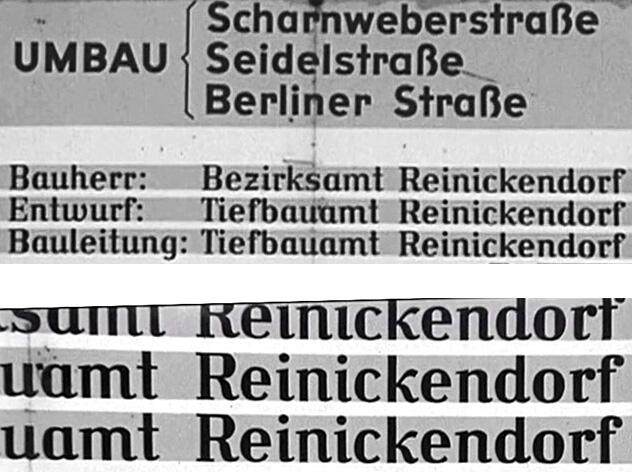
Bauschild-Schrift von 1960/61
Ich würde gern ein Bauschild aus dem Jahr 1960 (oder 61) digital "nachbauen", da leider keine gute Qualität in SW vorliegt.
Leider bin ich auch nach Ausprobieren dreier verschiedener Fontfinder (whatfontis, whatthefont und fontmatcherator) nicht annähernd fündig geworden.
Häufig wird ja bei der Suche nach älteren Schriften darauf verwiesen, daß es sich um Arbeiten eines Schildermalers handelte, was ja auch oft gut erkennbar ist an den teilweise sich unterscheidenden Formen eines im Text wiederkehrenden Buchstaben, z. B. e usw.
Auf den Ausschnitten (siehe Screenshot) des Bauschildes wird der Name "Reinickendorf" 3x untereinander wiederholt. Ich - als Laie - vermag hier keine Abweichungen einzelner Buchstaben von Zeile zu erkennen ... Daher gehe ich eigentlich nicht von einer Schildermaler-Schrift aus.
Augenfällig sind meiner Ansicht nach das unten leicht geschwungene kleine "w" im Wort Entwurf und der kleine Buchstabe "k", aber auch das kleine z mit Querstrich fällt zumindest heutzutage auf.
Auch hinsichtlich der serifenlosen Fettschrift am Kopf des Schildes "UMBAU" + 3 Straßennamen bin ich in keinem Fontfinder fündig geworden.
Besonders das runde a und das r mit dem nach unten gezogenen Bogen fallen hier auf. Runde a wurden hauptsächlich in Kursivschriften angezeigt, aber keine davon ähnelte auch nur ansatzweise der hier verwendeten Schrift.
Schilderhersteller nutzten aber auch Schablonen und dann sind wieder alle Buchstaben gleich.
Es spricht also trotzdem viel für eine Einzelanfertigung. Benannte Druckschrift druckte man in aller Regel auf Papier, was hier sicherlich nicht der Fall ist.